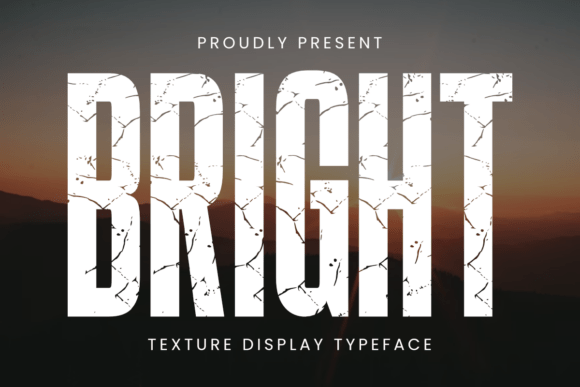
Bright
Bright: A Fonte Texturizada que Transforma Seu Design
Se você está em busca de uma tipografia que una força, personalidade e um toque vintage, Bright é a escolha perfeita. Essa fonte display ousada traz uma textura desgastada e rachada que confere um visual robusto e cheio de atitude a qualquer projeto.
- Textura Distressed: linhas quebradiças e rachaduras que dão a impressão de um material envelhecido.
- Impacto Visual: traços grossos que garantem alta legibilidade mesmo à distância.
- Versatilidade: ideal para pôsteres, capas de álbuns, gráficos esportivos, branding de aventura, design de vestuário e muito mais.
- Estilo Vintage: mistura perfeitamente o passado rústico com a modernidade do design.
Por que Bright se destaca no mercado?
Bright não é apenas mais uma fonte “grunge”. Ela foi desenvolvida para transmitir poder e personalidade em projetos que precisam de uma presença marcante. Seu design texturizado cria profundidade e dinamismo, tornando cada palavra uma peça de arte visual.
Aplicações Ideais
- Cartazes promocionais de eventos esportivos ou musicais.
- Capa de álbuns de rock, metal ou indie que buscam uma estética crua.
- Identidade visual de marcas de aventura, outdoor e lifestyle.
- Estampas de camisetas, bonés e produtos de moda streetwear.
- Design de logotipos que precisam de um toque agressivo e impactante.
Bright entrega exatamente o que promete: uma tipografia forte, texturizada e pronta para fazer sua mensagem brilhar em meio à multidão. Seja para projetos digitais ou impressos, ela garante que seu design se destaque com autenticidade e estilo.